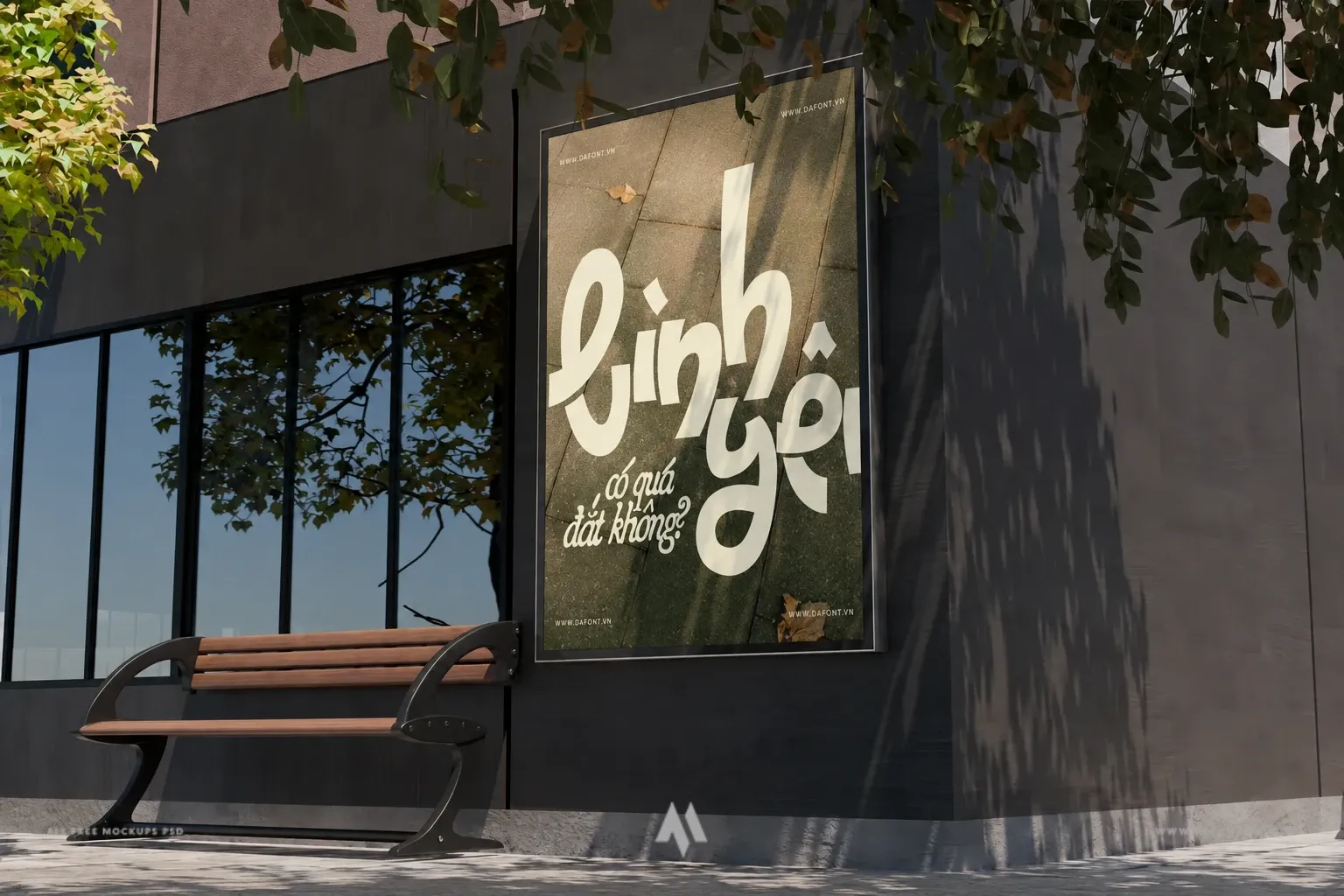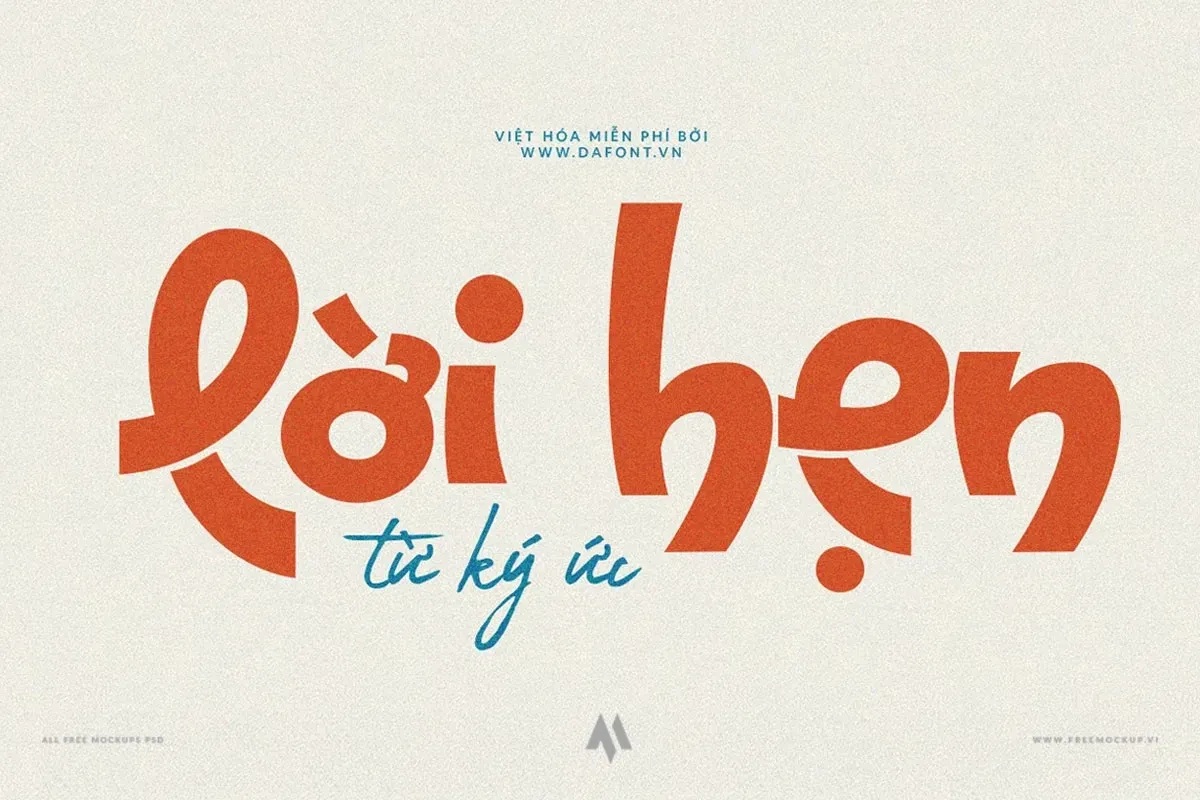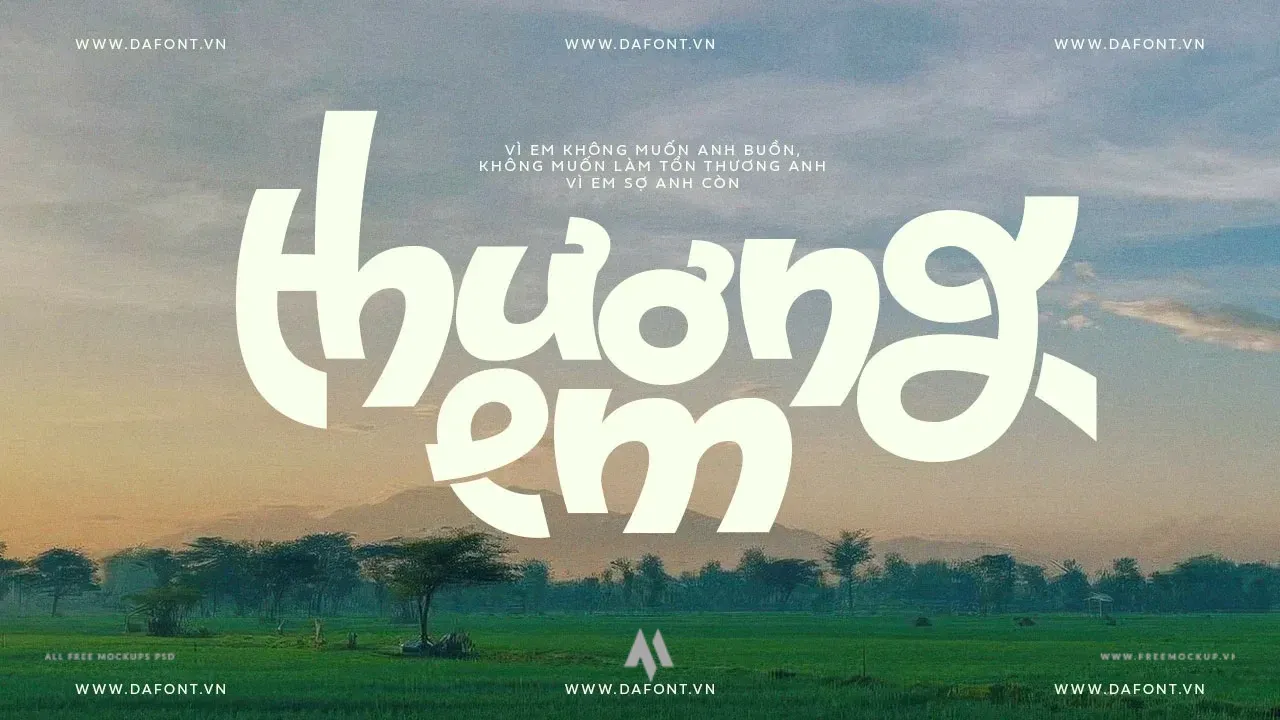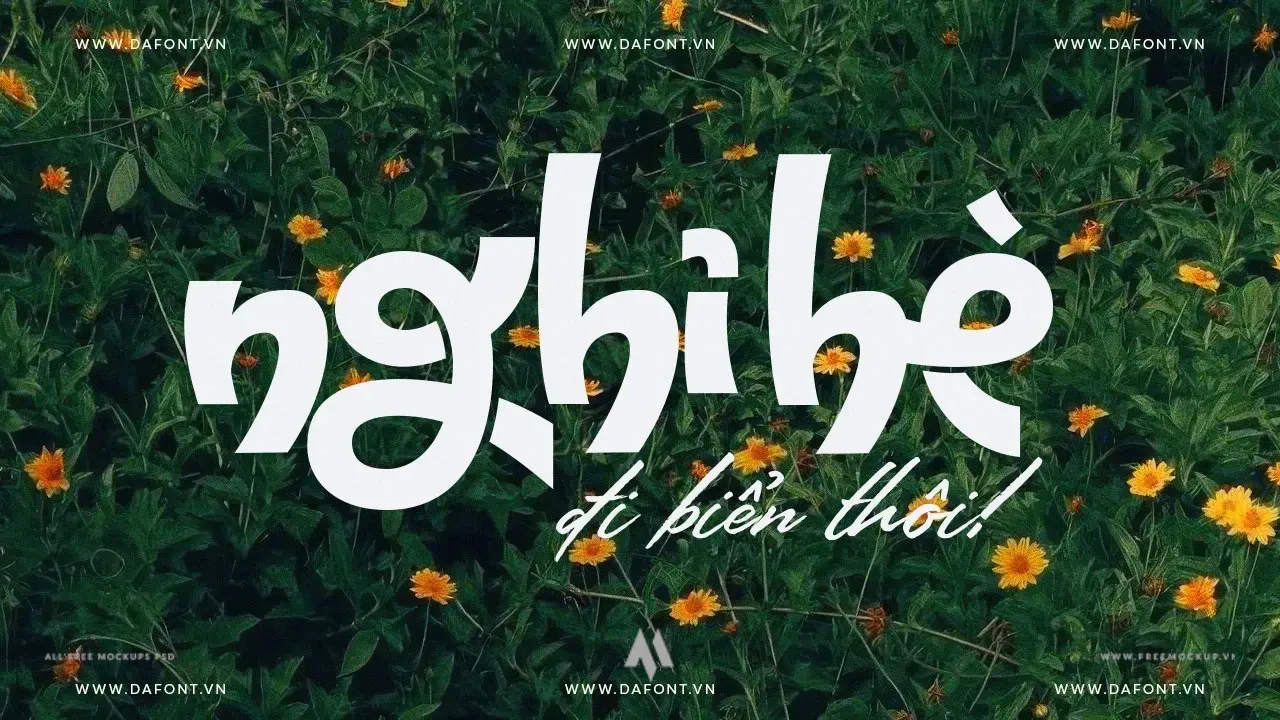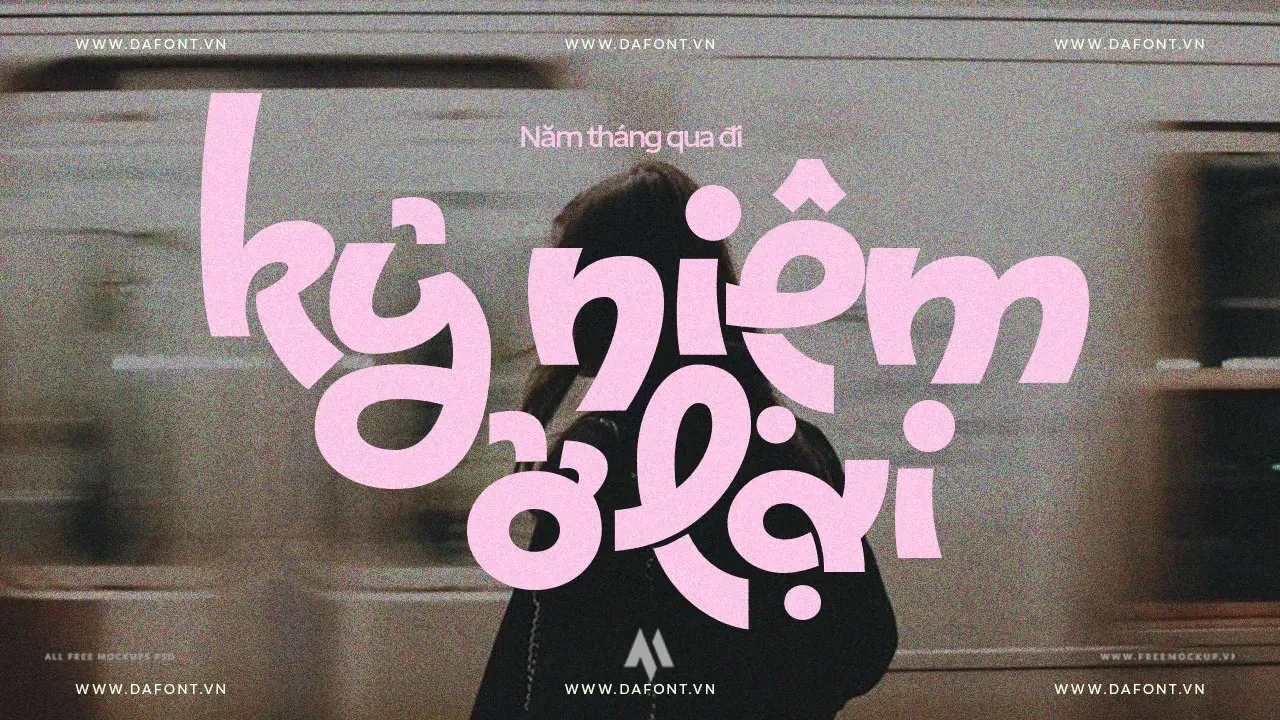
Giới thiệu về font chữ Hangout (Quarantype Hangout)
Hangout, hay tên gốc đầy đủ là Quarantype Hangout, là một kiểu font chữ hiển thị (Display/Decorative font) cực kỳ ấn tượng. Font sở hữu:
- Đường nét đậm nét, chắc chắn: Giúp tiêu đề hay thông điệp luôn nổi bật ở mọi kích thước.
- Đường cong tinh nghịch, vui nhộn: Tạo cảm giác trẻ trung, hiện đại và tràn đầy sức sống.
- Tính ứng dụng cao: Rất phù hợp cho các thiết kế poster, bao bì, banner mạng xã hội, áo thun, hoặc các dự án sáng tạo cần điểm nhấn mạnh mẽ.
Bản Việt hóa hoàn chỉnh từ DFVN
Thời gian qua, Hangout là một trong những font chữ “làm mưa làm gió” và được cộng đồng thiết kế sử dụng rất nhiều trên nền tảng Canva.
Nhận được sự quan tâm và yêu cầu lớn từ cộng đồng, team DFVN đã tiến hành Việt hóa trọn bộ font chữ này với:
- Đầy đủ dấu tiếng Việt chuẩn thẩm mỹ, không lỗi hiển thị.
- Căn chỉnh kerning kỹ lưỡng, giữ nguyên tinh thần gốc của tác giả.